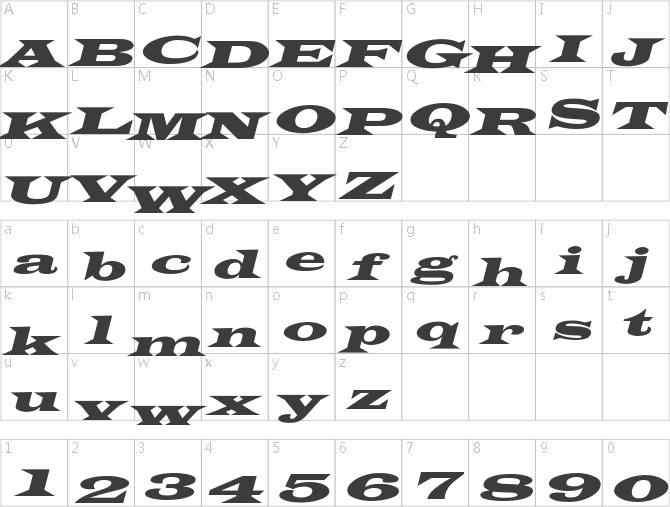
James-WideExtObl-Normal 詳情頁(yè)
James-WideExtObl-Normal字體字庫(kù)是一款讓人賞心悅目、百看不厭的英文字體,適合各類廣告和產(chǎn)品包裝設(shè)計(jì)應(yīng)用,字體大小0.06MB,格式為ttf字體,上傳用戶是素年錦時(shí),作者/版權(quán)方為未知